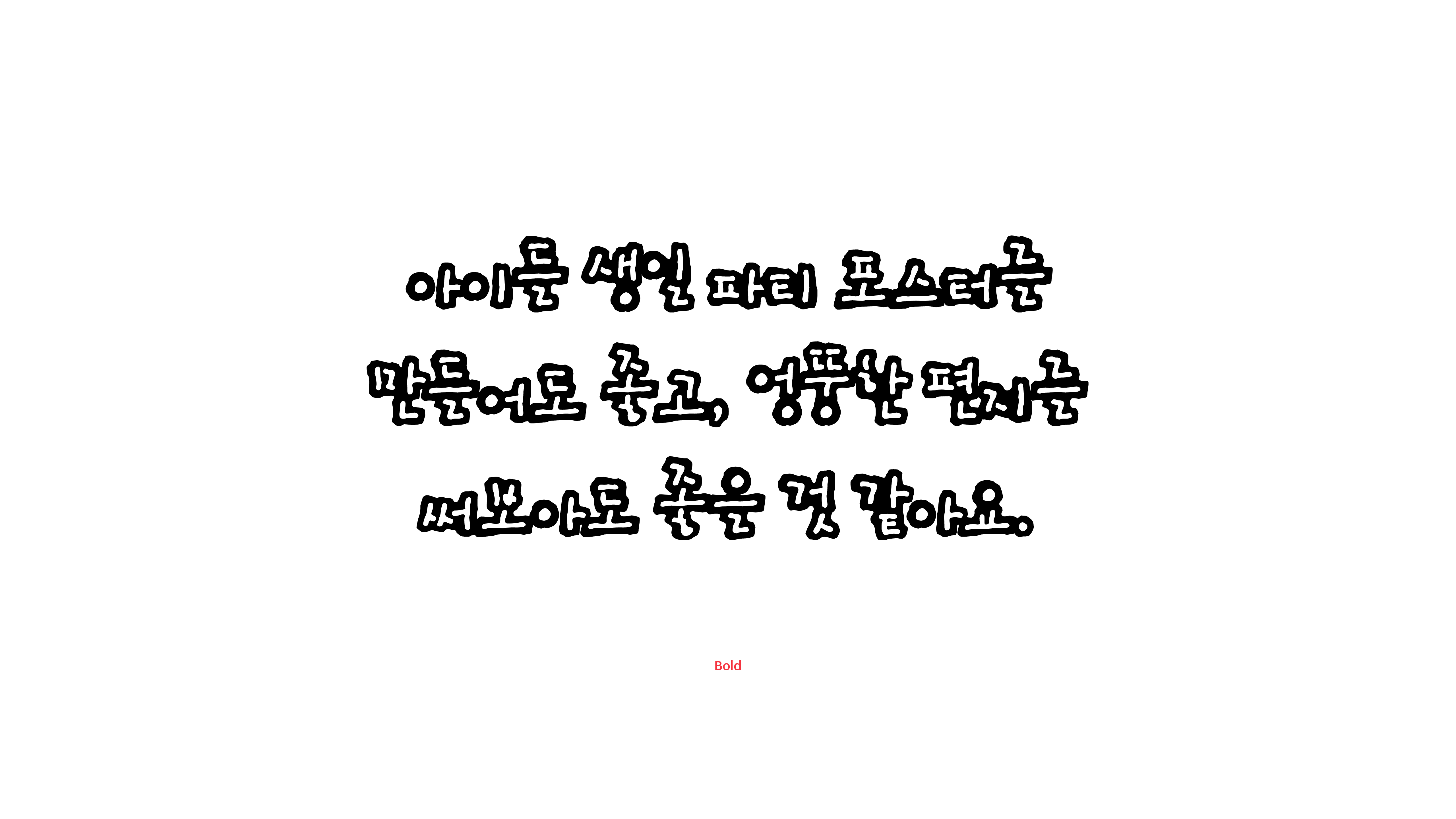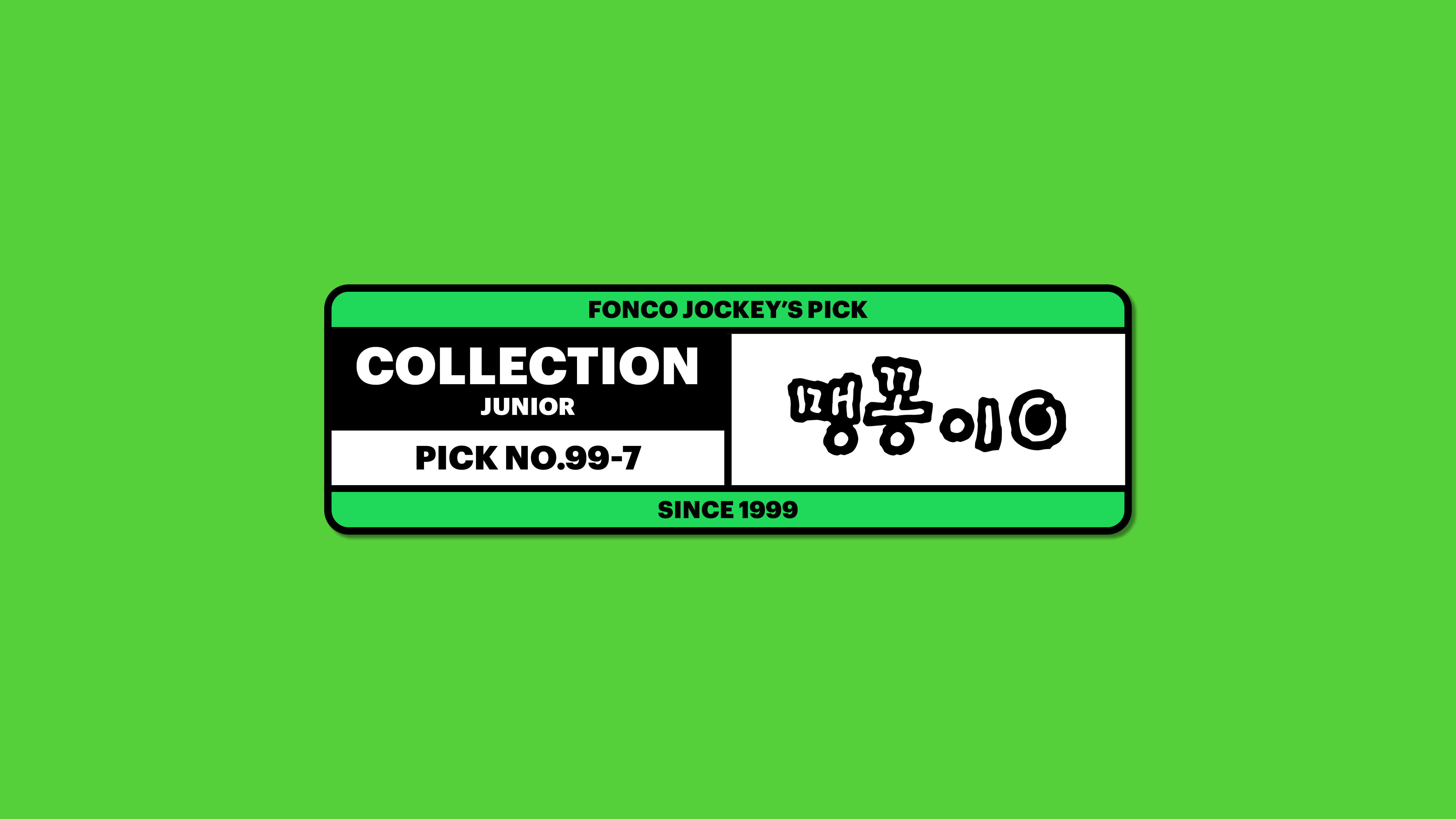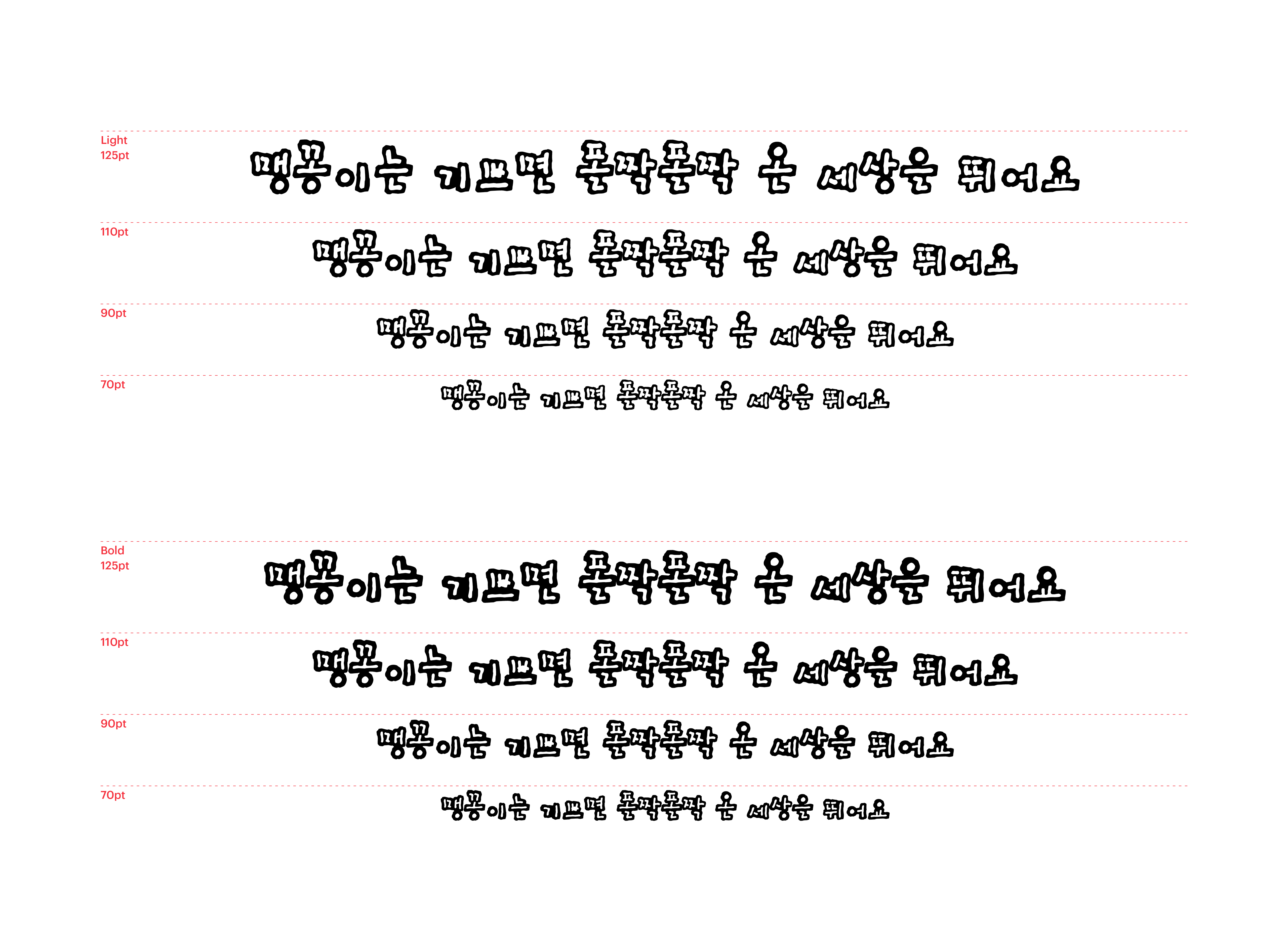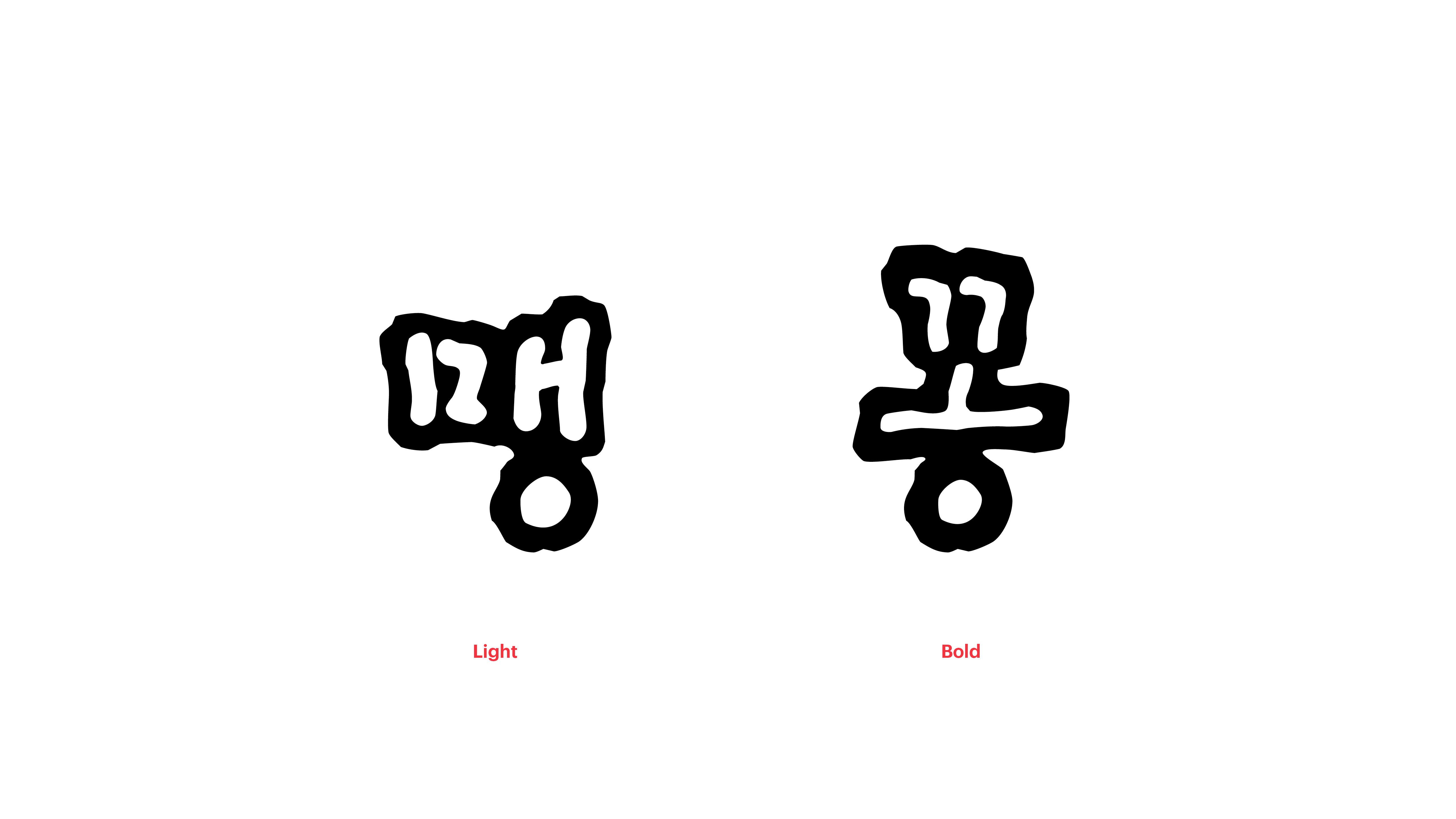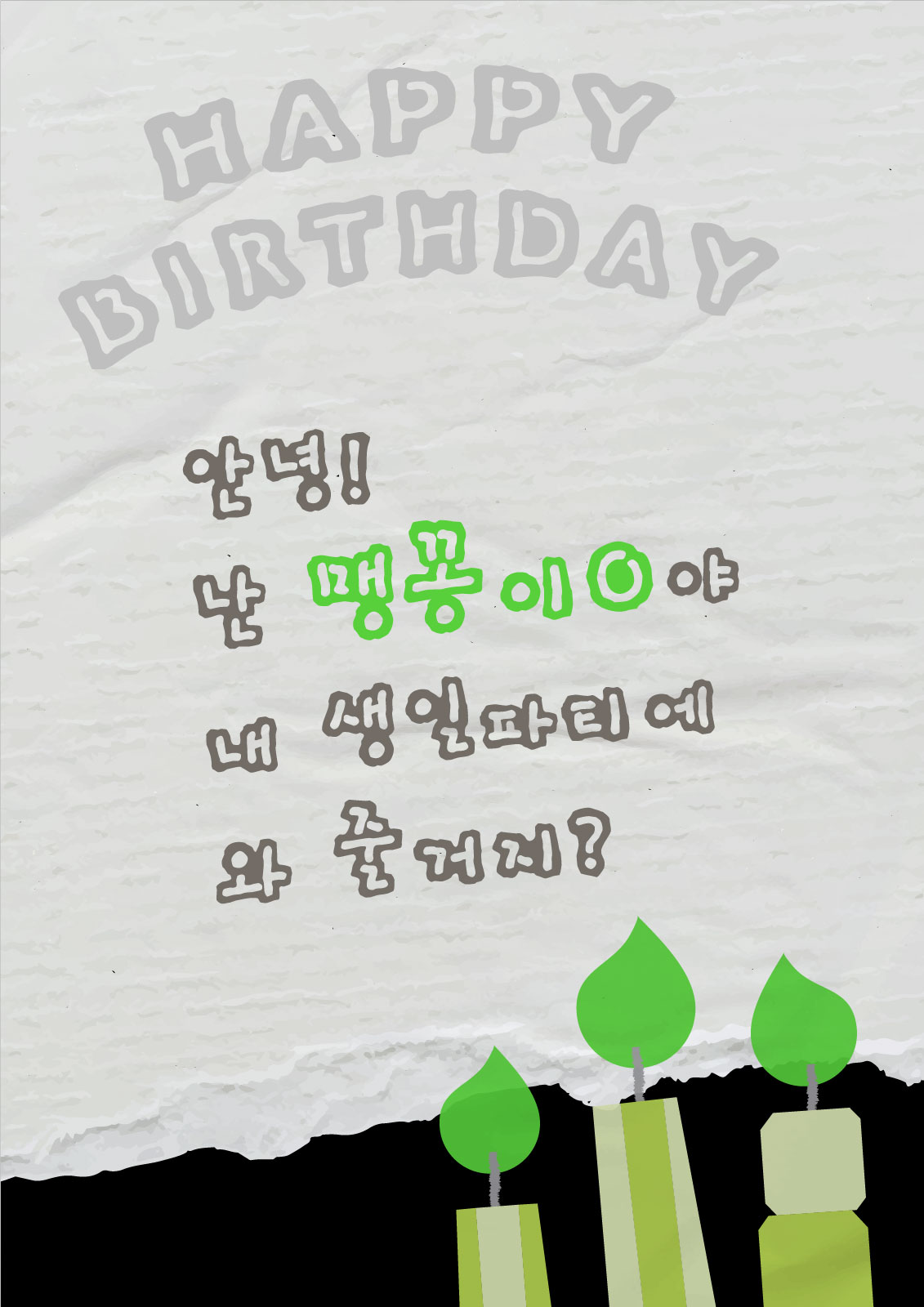
맹꽁이O
Yoon 맹꽁이O
맹꽁이Outline체는 맹꽁이체에서 테두리만 남기고 안쪽을 비운 폰트입니다. 이왕이면 더 다양한 곳에 사용할 수 있도록 재미있는 표현법을 추가해본 것이지요. 아이들 생일 파티 포스터를 만들어도 좋고, 엉뚱한 편지를 써 보아도 좋을 것 같아요. 맹꽁이Outline체와 함께, 나만의 특별한 기억을 디자인해보세요.